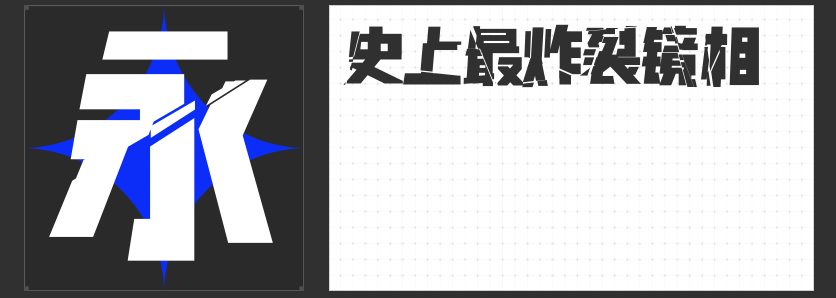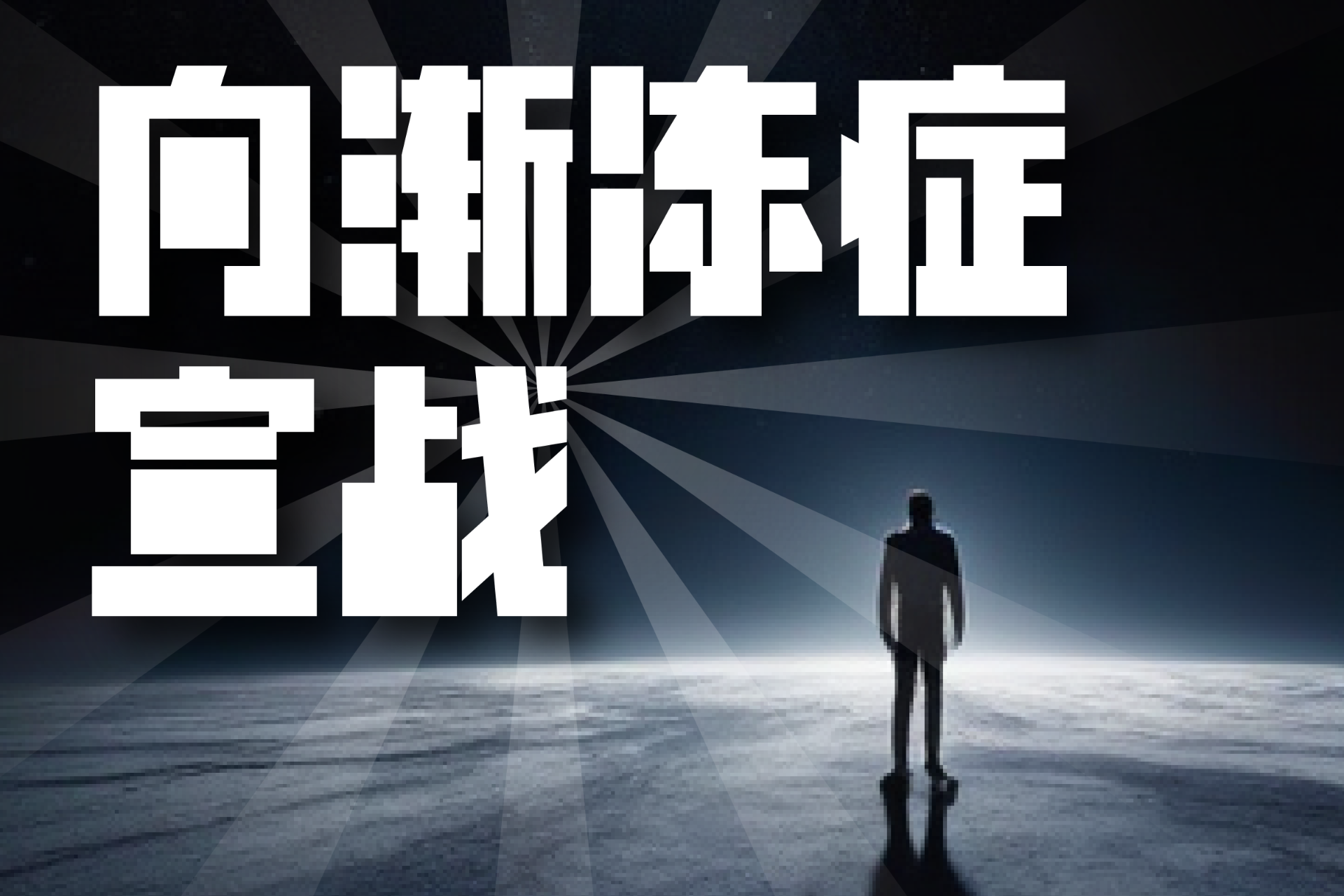
四款高辨识度字体推荐:以设计张力赋能商业表达
在商业设计中,字体不仅是信息载体,更是品牌调性的视觉化身。以下四款个性鲜明的字体,以突破常规的设计语言,为需要强烈风格化的项目提供创意解决方案。
一、励字暴风简 超级黑
这款字体以黑体为基底,通过“横竖梯形笔画”与“粗细不均等处理”打破传统黑体的秩序感。笔画转折处呈现锐利棱角,撇捺笔画的梯形切割更强化了字体的工业气质,适用于科技产品发布会主视觉、现代艺术展览海报等场景。其笔触间的不规则留白,在放大使用时能形成独特的视觉呼吸感,尤其适合作为标题与英文衬线体混排,凸显先锋品牌调性。
二、励字多重人格简
受影视分镜美学启发,这款字体通过“碎裂镜像滤镜”模拟人格分裂的视觉张力。字符边缘呈现不规则炸裂纹理,字间距的错位排列进一步强化了排版动感,是悬疑类电影海报、音乐节主视觉的利器。当与渐变色彩或光效叠加时,能营造出赛博朋克风格的未来感,但需注意在正文排版中避免过度使用,以防削弱信息可读性。
三、励字魔方黑简
以“方头方尾”笔形构建的励字魔方黑简,通过横竖笔画3:1的粗细对比,形成极具记忆点的视觉符号。其无衬线设计在户外广告牌、快消品包装等远距离阅读场景中表现优异,字符间距的精密计算也确保了在小字号下的清晰度。这款字体既能驾驭奢侈品牌的极简美学,也能通过金属质感处理适配工业风设计,堪称商业设计的“瑞士军刀”。
四、喵字渐冻体
这款为渐冻症公益项目定制的字体,通过“笔画冻结”效果模拟患者肌肉僵化过程——字符从左至右逐渐呈现笔画粘连、锐角钝化特征,形成独特的动态残缺美。在医疗健康类APP界面、公益宣传物料中使用时,能以隐喻手法传递疾病认知,其设计深度超越了常规展示功能,更适合需要情感共鸣的叙事型设计。